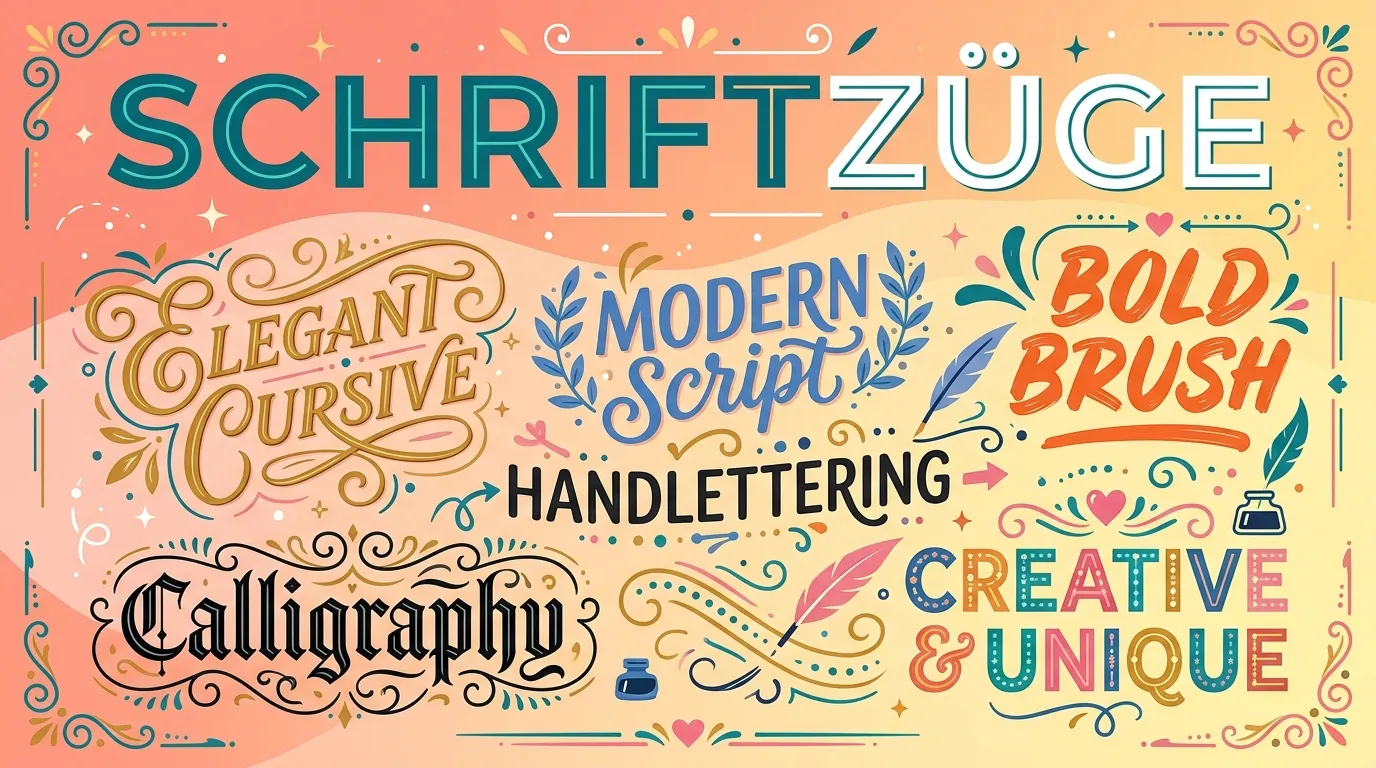
Schriftzüge Generator
Gestalte deinen Text als einzigartigen Schriftzug: zum Kopieren für Social Media oder als Bild-Export für Tattoo, Poster und Druck. Kostenlos, ohne Anmeldung, direkt im Browser.
Umlaut-Garantie für den DACH-Markt
Jeder Stil wurde einzeln auf die korrekte Darstellung von ä, ö, ü und ß getestet. Stile mit eingeschränkter Umlaut-Unterstützung sind transparent gekennzeichnet.
Hinweis: Umlaute (ä, ö, ü, ß)
Deutsche Umlaute und ß haben keine Schriftzüge-Entsprechung im Unicode-Standard und erscheinen daher in normaler Schrift neben den umgewandelten Buchstaben. Das ist eine unvermeidliche technische Einschränkung aller Schriftzüge-Generatoren, nicht ein Fehler unseres Tools.
Schriftzüge für jeden Anlass gestalten
Ob elegante Schreibschrift für die Hochzeitseinladung, ein kräftiger Blockschriftzug für das Geburtstagsbanner oder ein verschnörkelter Name für das Instagram-Profil: unser Generator bietet über 100 Stile für jeden Anlass. Besonders beliebt sind Schriftzüge für personalisierte Geschenke, Wandtattoos und Namensschilder.
Anders als bei vielen Wettbewerbern haben wir jeden Stil einzeln auf korrekte Darstellung deutscher Umlaute (ä, ö, ü, ß) getestet und kennzeichnen transparent, welche Stile diese Zeichen unterstützen.
Neben Buchstaben lassen sich mit unserem Tool auch Zahlen in kreativen Schriften gestalten : ideal für Countdowns, Jubiläen und Gaming-Profile.
Unicode-Text vs. Bild-Export: wann nutze ich was?
Der Unicode-Modus erzeugt kopierbaren Text, der überall funktioniert, wo du normalen Text eingeben kannst: Instagram-Bio, WhatsApp-Status, TikTok-Profil, E-Mail-Signaturen. Der Vorteil: keine Installation, kein Download, sofort nutzbar.
Der Bild-Export (PNG) ist ideal, wenn du den Schriftzug drucken willst (Poster, Einladungen, Namensschilder) oder als Vorlage für einen Tätowierer benötigst. Auch für Anwendungen, die keine Unicode-Sonderzeichen unterstützen (z. B. manche E-Mail-Programme oder Formulare), ist der Bild-Export die sichere Wahl.
Tipp: Probiere beide Modi aus: manchmal sieht ein Stil als Bild ganz anders aus als im Unicode-Text.
Schriftzüge für Tattoos, Poster und Wandtattoos
Unser Bild-Export erzeugt hochauflösende PNG-Dateien, die sich direkt als Tattoo-Vorlage verwenden lassen. Für Wandtattoos und Poster empfehlen wir dunkle Schrift auf transparentem Hintergrund: so kann dein Druckdienstleister den Schriftzug auf jede Oberfläche anpassen.
Wichtig: Für professionelle Tattoo-Vorlagen empfehlen wir, den generierten Schriftzug als Ausgangspunkt zu nutzen und mit deinem Tätowierer die finale Vorlage abzustimmen. Filigrane Linienstärken und sehr kleine Schriftgrößen können mit der Zeit auf der Haut an Lesbarkeit verlieren.